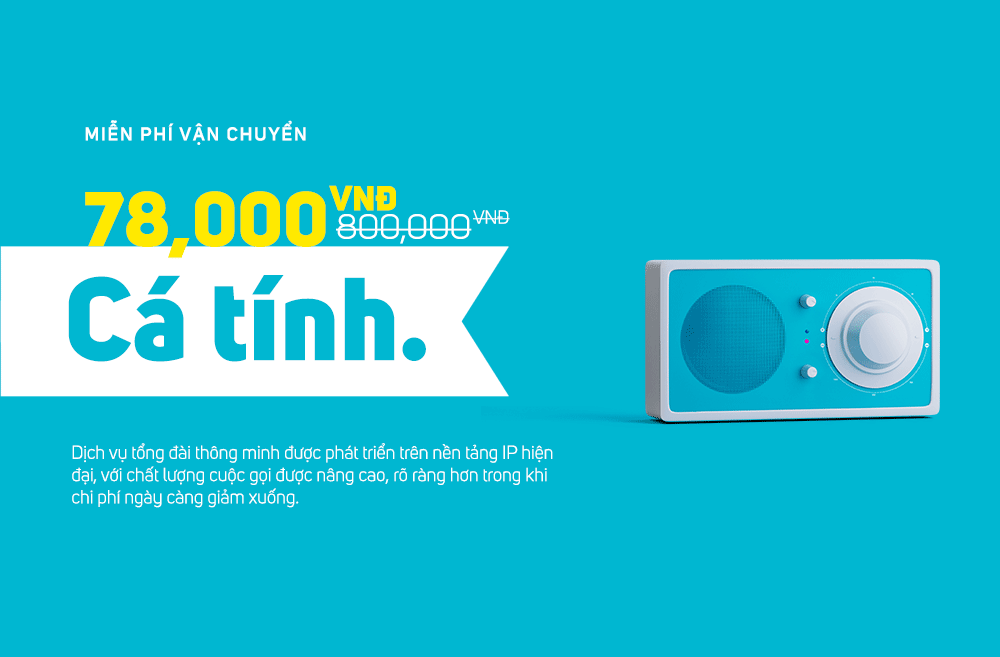
[Sans-serif] Uni Sans Việt hóa
Thông tin về font Uni Sans
Được thiết kế cực kỳ dễ đọc trong cả hai lĩnh vực - in ấn và thiết kế web, hình học của Uni sans được nghiên cứu một cách kĩ càng, kerning được chỉnh bằng tay, nó là giải pháp hoàn hảo cho web và các ấn phẩm của bạn.
Lấy cảm hứng từ những bộ font kinh điển như Din và Dax, Uni Sans vẫn có những nét đặc trưng mà chỉ nó mới có như những nét bo tròn hình học hoàn hảo. Cả font family phù hợp nhất cho việc thiết kế tựa đề, cũng như đoạn văn bản cả kích cỡ lớn lẫn nhỏ.
Uni Sans có thể dùng hầu hết trong mọi thiết kế, từ web, in ấn, đồ họa tĩnh, đồ họa động, hoàn hảo cho thiết kế áo phông và những vật phẩm khác như bao bì, poster, logo...